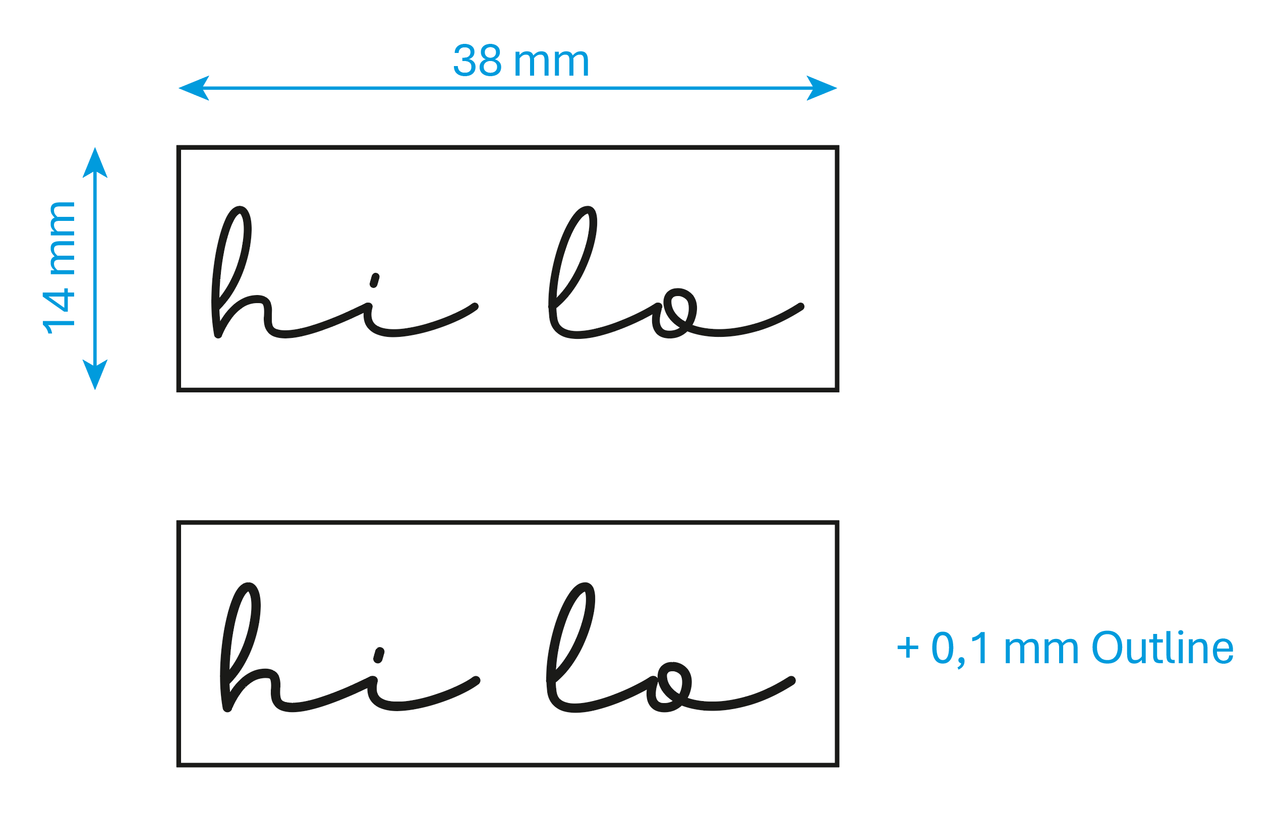
Unsicher ob Font die richtige Wahl für Textilstempel ist?
ich möchte für mein sich in Gründung befindendes kleine Label einen Textilstempel anfertigen lassen. Als Schriftart hat es mir vor allem Alagambe angetan. Der Name des Labels besteht nur aus 4 Buchstaben.
Alagambe ist relativ dünn und eine dicke Version nicht verfügbar.
Ich habe ansonsten noch die Schrift Sarina, die mir gefällt, die aber wieder viel zu dick ist.
Bin leider am verzweifeln die richtige Schrift zu finden, die mir wirklich gefällt.
Habt ihr einen Rat?
Gleiches ginge auch bei der Sabrina, ich nehme an, die willst Du auch via Dafont nutzen, doch die haben einen Sack voller Schriften mit dem Namen Sabrina.
In welcher Stempelplattengröße?
Wenn nur 4 Buchstaben und beispielsweise eine Standardgröße von Trodat 38 x 14 mm verwendet werden, kommt das auch mit der Alagambe schon gut hin. Zusätzlich könntest du die Schrift händisch ein wenig auffetten. Und man darf nicht vergessen, dass die Abbildung auf einem Stoff zusätzlich ein wenig verläuft, also im Ergebnis noch fetter wird, als sie angelegt wurde.
Rahmstärke ist zum Vergleich mit 0,25 mm = 0,7 pt angelegt.
Genau, der Stempel ist so ein Standartformat von 38x14 mm.
@Diwarnai Wie kann ich denn diese Schriftart händisch auffetten? Bei den Programmen, die ich habe, ist die Option leider nicht wählbar, und ich dachte das liegt am Font selber. Freue mich über einen Tipp! :)
Da klingt für mich ein wenig Linux mit.
Im Gegensatz zu @Diwarnai bin ich kein Profi, doch vielleicht hilft Dir meine Idee weiter.
Da ich nicht weiß, welches OS Du verwendest, besorge ich mir Inkscape, denn Schriften sind Vektoren und daher brauch ich auch ein Vektorprogramm. Ich hab keine Ahnung, ob Canva Vektoren kann, denn ich nutze die Affinity-Programme, die es jedoch nur für Windows und MacOS gibt.
Dort schreibst Du dann Deinen Text, markierst ihn, drückst strg+umschalt+f und wechselst zu Kontur und spielst dort mit den Reglern, bis Dir das Ergebnis gefällt :)